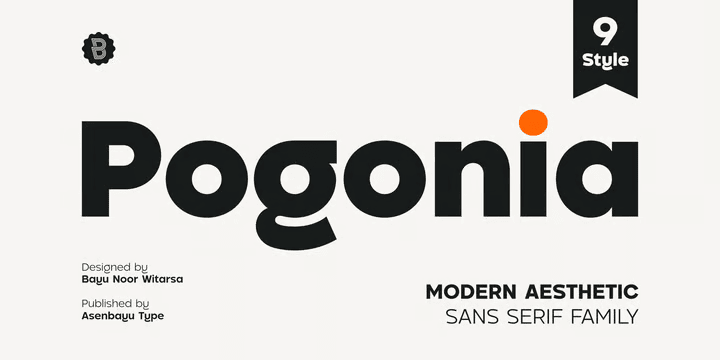
スッキリとしたクリーンなジオメトリックサンセリフ。ジオメトリックではあるがヒューマニストの風味も多分に加味されており、大変モダンかつクリーンでしかも読みやすい。これからのスタンダードになり得ると思わせてくれる(言い過ぎ?)非常に質の良い書体である。たいへん偉そうな言い方にはなるが、一見日本人が作ったとはとても思えないほどネイティブなニュアンスを持っており、ラテン文字を母語(母字?)としない人間がここまで来るには相当な努力があったのではと思う。素晴らしい書体が誕生した。イタリックもあって8ウェイト。
ソフトでフレンドリーなサンセリフディスプレイ。柔らかな印象のポップなサンセリフで、アウトラインの角が丸くなっているほか、斜めのストロークがくっと曲がってアーチ状になっているのが特徴。A や R など頭でっかちなプロポーションがかわいらしさを演出している。子供向けや食品・スイーツなどと相性が良さそう。イタリックはないが8ウェイトあり。ただいま30%オフセール中。
一昔前の近未来のイメージ(ややこしい)のあるサンセリフディスプレイ。ミニマムなジオメトリックのサンセリフをベースに、一部ステンシルのようにストロークを欠いてアクセントを付けている。全体的なイメージがレトロ SF な感じがあって、モダンとレトロが融合したような書体である。小文字の s がベースラインに埋まっているのが特徴。ストロークが欠けてないオルタネートがある他、リガチャーも若干あり。イタリックもあって5ウェイト。
本日は『世界量子デー World Quantum Day』だそうなのでこちら。かなり幅広なディスプレイサンセリフ。幅広なだけで他にはこれといった特徴はない(笑)。昔の SF 映画などを見るとよくこの辺の幅広なサンセリフが使われている事が多く、当時は角張ってたりストロークの一部が欠けていたりというアレンジがなされていたが、この書体はそういった事はなく、普通の柔らかなサンセリフとなっている。イタリックはなく5ウェイト。
柔らかな印象のジオメトリックサンセリフ。元は Fibra という別の書体のアレンジで、アウトラインの角が丸くなっていてだいぶ目に優しいソフトな印象に仕上がっている。有名な書体 Avant Garde にインスパイアされたとあるが、全然アバンギャルドではなく(笑)、可読性が良くイタリックもあって長文にも十分耐えうる。a には1階建てのオルタネートがある他、t や l にはベースライン上で大きく曲がって判読性がよくなった Alt というバージョンがある。それぞれに8ウェイトで計32種。ただいま30%オフセール中。
変わったリガチャーが豊富なディスプレイサンセリフ。基本は若干コンデンス気味のジオメトリックサンセリフだが、大文字に見ての通りかなり変わったリガチャーが豊富にあり、個性的な文字組が楽しめる。やはり主にはロゴ用途だろう。ウェイトも9つもあるので、繊細な細いものから太く力強いものまで対応可能。この手はウェイト展開が弱いと目的に合致しない事があるので重宝すると思う。
グリフが簡略化されたおもしろシンプルなジオメトリックサンセリフ。見ての通り字形(グリフ)が簡略化されており、r などは単体で出されたらとても読めそうもない(笑)。ただこういうのは数文字並べればなんとなくルールが分かって読めるようになるのは不思議である。文を組むのはまったく向いてなく、代わりにロゴなどにはそのまま使えると思う。モダンなようでどことなくレトロな雰囲気を持っていて親しみやすい書体。5ウェイトある他、バリアブルタイプもあり。
カジュアルかつニュートラルでクセのないすっきりとしたヒューマニストサンセリフ。ややポップというかフレンドリーというか、そういう雰囲気のカジュアルなサンセリフで、可読性も大変良く日常使いには適したサンセリフ。a と g には1階建てと2階建てがあり、数字にはオールドスタイルもあり。ウェイトが太くなってもきちんと可読性は保たれており、なかなか優秀な書体である。イタリックがないのが残念だろうか。日用品のパッケージなどに。10ウェイト。
本日はダンロップ創業者ジョン・ボイド・ダンロップ John Boyd Dunlop(1840)とシトロエン創業者アンドレ・シトロエン André-Gustave Citroën(1878)の誕生日という事でこちら。レーシングサーキット風味の強い図太いサンセリフディスプレイ。車やバイクのレース場でよく見るような目立つサンセリフで、B が頭でっかちだったり、K のアームやレッグが垂直だったりといくつか特徴的なグリフがある。クランク型の S が特に面白いだろうか。画像には大文字しかないが小文字もちゃんとある。けどまあ大文字だけで使うのが普通かもしれない。販売サイトでは “Japanese” というタグが付いており、日本の’60~’70年代のデザインからインスパイアを受けたものと思われる。言われればそうかも。 1ウェイトのみ。